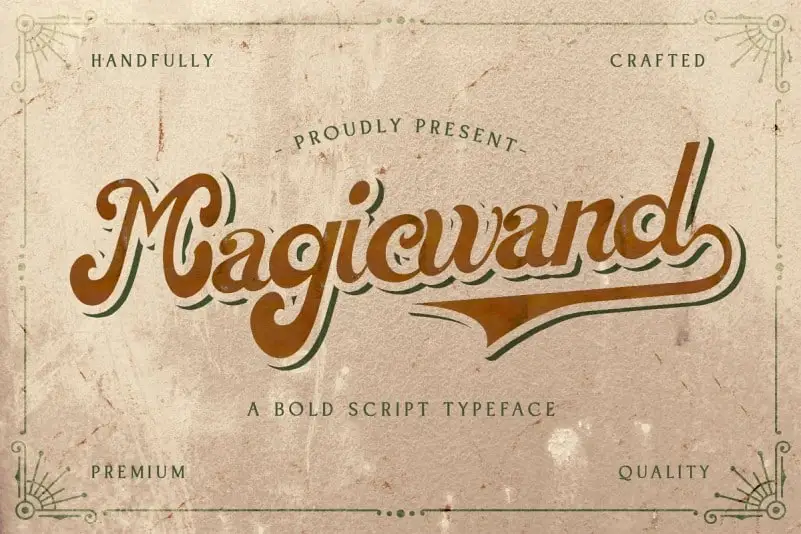
Magic Wand Script Font é uma fonte script que se destaca pela sua personalidade única. Ela foi criada pelo designer StringLabs para permitir múltiplas utilizações, desde logotipos e selos até cartões de agradecimento e convites de casamento. Sua principal característica são os caracteres fluidos, ideais para criar mensagens atraentes. Esta font é bold e possui um estilo retro e gótico, tornando-a perfeita para dar aquela pitada nostálgica especial em qualquer projeto gráfico que você possa imaginar. Seja para uma identidade visual ou para adicionar um toque de nostalgia ao seu design, Magic Wand Script Font é a escolha certa.